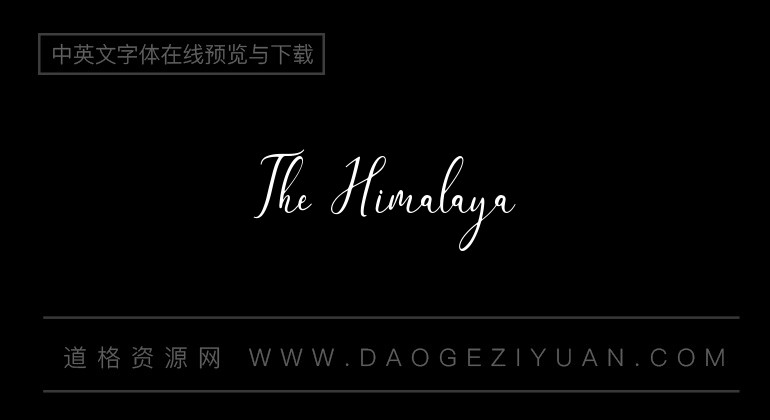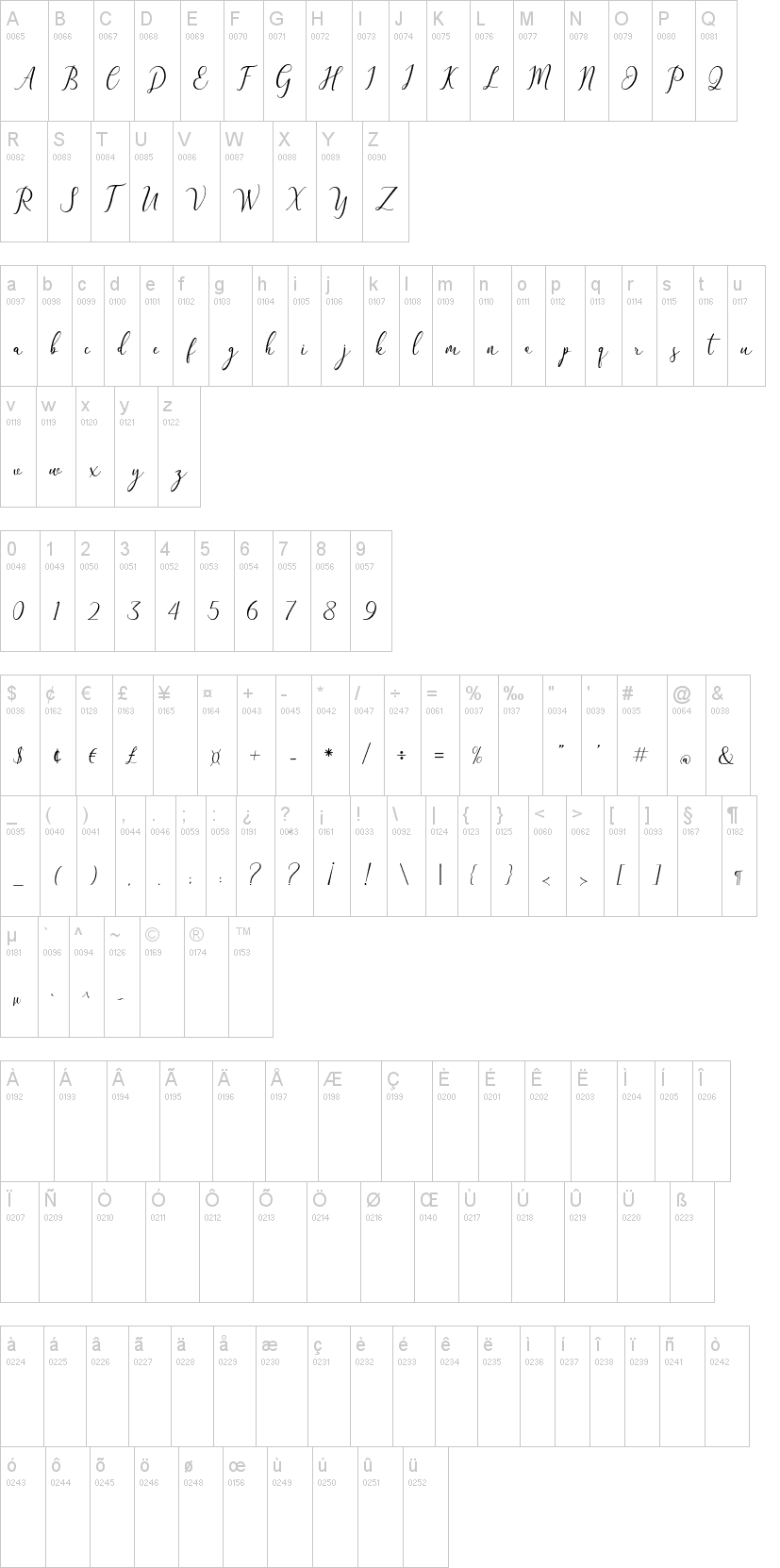
The Himalaya
The Himalaya 字体是一款具有清新古典风格的英文字体,它的设计灵感来自印度的喜马拉雅山脉,具有浓郁的古典风格,细节精致,且具有清新的感觉。The Himalaya 字体的字形曲线流畅,更具有优雅的气质,适合用于文字的排版和印刷,也可用于各种网页设计、图标设计等等。
The Himalaya是一款非常不错的手写艺术字体,具有很好的视觉感,适合于文化类的宣传设计、商业类品牌的广告和产品包装设计以及个性化文字排版等较多场景。
The Himalaya字符映射图